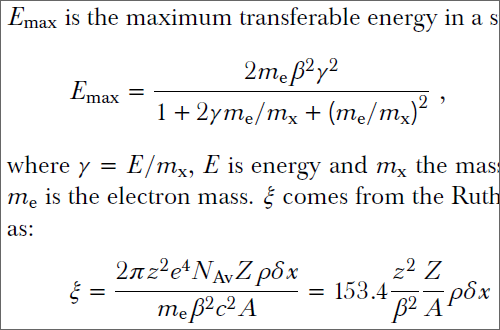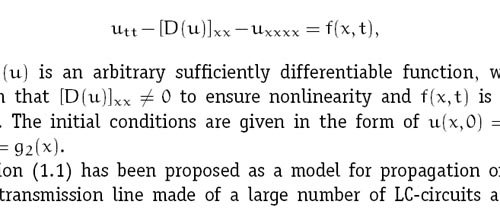
Erfahrungen mit HF&J Chronicle Text?
ich suche gerade (leicht verzweifelt) eine Schrift für einen mathematischen Text. Ich brauche also typischerweise griechische Buchstaben, Kapitälchen, einen deutlichen fetten Schnitt und vielleicht noch eine Small-Text-Variante.
Nach ein paar Fehlversuchen bin ich im Moment bei der HF&J Chronicle Text gelandet. Leider besitze ich die Chronicle (noch?) nicht und kann nicht mit ihr spielen. Habt Ihr irgendwelche Erfahrungen mit der HF&J Chronicle Text? Wäre es z.B. möglich die fehlenden griechischen Buchstaben aus der Georgia zu klauen? Welchen der vier möglichen "Grades" sollte ich wählen? Verträgt die Chronicle einen unruhigen, mit Formeln und Bildern durchsetzten Text?
p.s.: Anbei noch meine bisherigen Fehlversuche:
• Arno, naja die ist mein derzeitige Wahl, aber wenn ich sie wirklich wollte, müsste ich nicht hier um Rat fragen. Ich mag halt eher rationale Schriften.[/*:m:cjaa8vde]
• Stormtype Baskerville Ten: Baskerville und ich werden keine Freunde. Irgendwie finde ich nicht die passende Zeilenlänge und -abstand. Zudem ist sie nicht gerade platzsparend, und dann die extravagante Kursive. Schade, denn ich mag sie wirklich gerne![/*:m:cjaa8vde]
• National mit griechischen Buchstaben aus der Corbel funktioniert in meinen Augen überraschend gut, ist aber für konservative Ingenieure und Mathematiker wohl zu extravagant. Außerdem tippe ich, dass die Großbuchstaben für den Formelsatz zu klein sind.[/*:m:cjaa8vde]
• Palatino, ich habe die Palatino schon für mathematische Texte verwendet, klappt als Vernunftlösung ziemlich gut, aber ich kann die Palatino (und andere Zapf-Schriften) nicht leiden.[/*:m:cjaa8vde]
• Minion, eigentlich sollte sie mir gefallen, aber wenn ich sie tatsächlich verwende, dann ... ach ich weiß auch nicht, also keine Minion.[/*:m:cjaa8vde]
• FF Celeste, ist mir irgendwie zu "weiblich" für einen Ingenieurstext (finde nicht die richtigen Worte).[/*:m:cjaa8vde]
• Computer Modern ist potthässlich und magersüchtig.[/*:m:cjaa8vde]
• Thesis, schon der Name sagt, dass sie geeignet ist, aber ich habe keine Thesis (Sans, Antiqua B), folglich fehlt mir die Erfahrung.[/*:m:cjaa8vde]
Was ist denn mit der Fedra? Da gibt es doch eigentlich fast nichts, was es nicht gibt. Oder ist die zu teuer?
Alternativ vielleicht Anselm/Anselm Sans? Wenn Du, wie Du schreibst, von vornherein davon ausgehst, daß die Chronicle Text nicht alle Zeichen beinhaltet, die Du benötigst, dann würde ich sie auch nicht nehmen.
[*]Computer Modern ist potthässlich und magersüchtig.
Was ist denn mit der Fedra? Da gibt es doch eigentlich fast nichts, was es nicht gibt. Oder ist die zu teuer?
Die Fedra hat a bisele zu viel Charakter. Auch die Anselm ist ebenfalls ziemlich auffällig und für einen Ingenieurstext zu weich. Da der Text von Natur aus schon unruhig ist (Formeln, Grafiken, Marginalien, ...) brauche ich etwas Unauffälliges. Insbesondere soll sich die Kursive unauffällig in den normalen Text integrieren, da ich nicht einzelne Wörter hervorheben will, sondern eher ganze Textpassagen (z.B. Definitionen). Trotzdem danke für den Tipp, bin für neue Ideen immer offen.
Die Comenia von Stormtype als Alternative zur Anselm passt richtig gut, aber dummerweise wieder keine griechischen Buchstaben ... Mist.
Wenn Du, wie Du schreibst, von vornherein davon ausgehst, daß die Chronicle Text nicht alle Zeichen beinhaltet, die Du benötigst, dann würde ich sie auch nicht nehmen.
Vernünftige Argumente werden stark überschätzt :blabla:, die Chronicle ist doch sooo schön. Momentan habe ich noch die Hoffnung, dass man Chronicle und Georgia verheiraten kann, aber einfach blind die Chronicle kaufen möcht ich auch nicht. Im Notfall dann doch die Arno.
Was für eine Publikation soll das denn eigentlich werden? Ich wundere mich gerade, daß z.B. die Federa »zu viel Charakter« haben soll. In den mathematischen Fachjournalen, die ich mir auf die Schnelle angesehen habe, finden durchaus noch viel »charakterstärkere« Fonts Verwendung. Diese Mischung aus dem Journal of Applied Mathematics finde ich z.B. gerade ziemlich abgedreht:
Das kommt doch auch immer auf den Satz an. Warnock Pro kann ich noch empfehlen. Die hat in größeren Lesegeraden aber auch ziemlich viel Eigencharakter. Das Journal of Biological Chemistry setzt aber in 9 pt oder so, da fällt das z.B. überhaupt nicht auf sondern läßt sich einfach recht gut lesen. Wenn man da natürlich in 12 pt mit doppeltem Zeilenabstand ran geht, dann fällt das natürlich schon eher auf. :wink:
Also, wofür ist’s denn gedacht? :?
Also, wofür ist’s denn gedacht?
Momentan ist es eine private typografische Fingerübung zum Thema Eulerwinkel mit etwa 40 Seiten. Falls es gut klappt, sollen verschiedene weitere Parametrisierungen von Drehbewegungen folgen und eventuell ein Buch entstehen. Zielgruppe und kritischer Leser bin erstmal ich, aber die sehr unfertige Beta-Version ging schon Arbeitskollegen, verschiedene Diplomanden und teilweise sogar Kunden. Eigentliches Ziel ist die typografische Vorbereitung meiner Dissertation, aber da ist noch viel Zeit.
Wenn Dir die Baskerville grundsätzlich gefällt und die Kursive doch nicht so wichtig ist, könntest Du Dir auch mal die Baskerville von Micropress anschauen. Die ist von Bertholds Baskerville abgeleitet, besitzt passende mathematische Zeichen, und ich glaube, sie läuft ein weniger schmaler als die Baskerville Ten. (Sie hat allerdings auch nur eine Entwurfsgröße, und ich habe auch keine Erfahrung mit der Schrift.) Ein Beispiel: